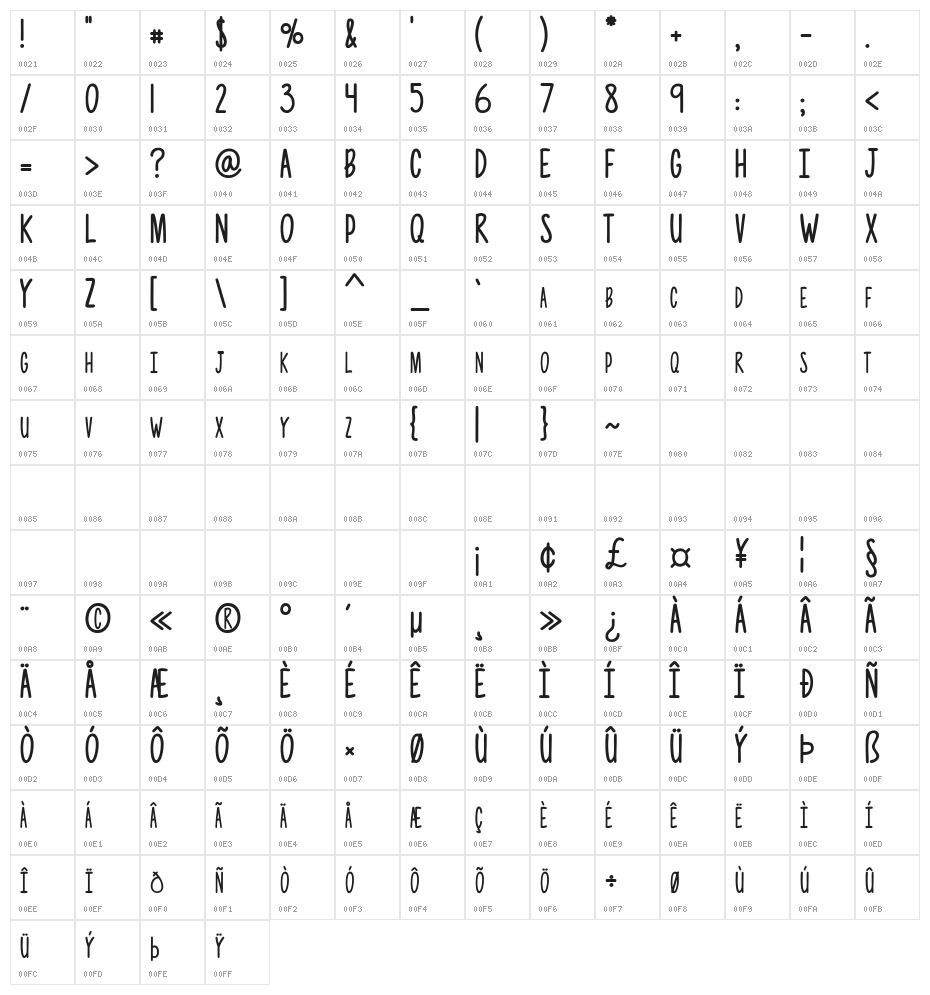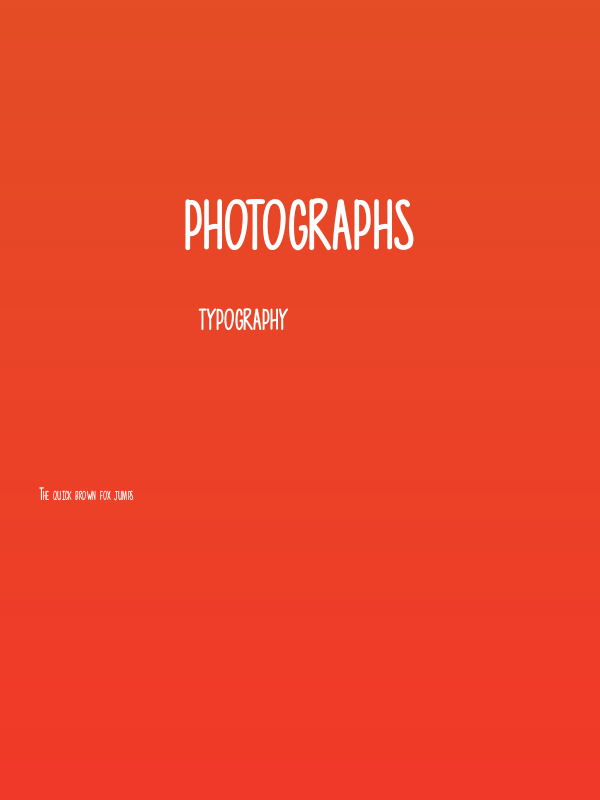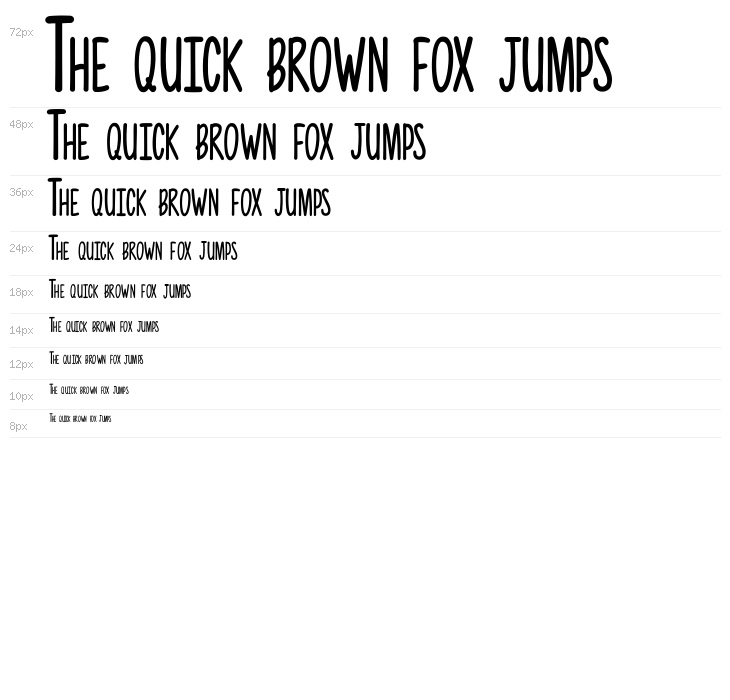
Photographs Font
| Estilo general | Casual, Playful |
| Caso de uso | Headlines, Logos, Invitations |
| Proyectos propuestos | Ideal for greeting cards, children's books, playful branding, and casual invitations. |